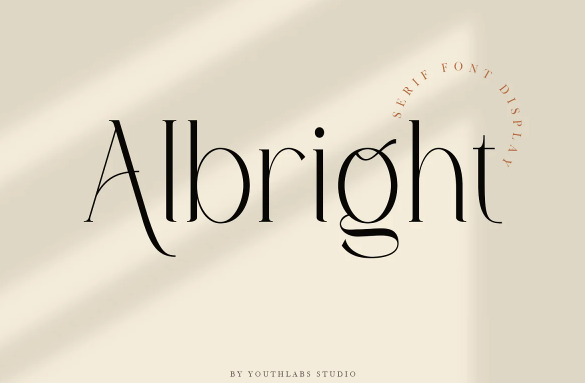
[Creativemarket] Albright Font (2021)
Шрифт Albright - это шрифт SERIF, который демонстрирует современную элегантность с уникальными лигатурами и альтернативами для дизайнера или владельца продукта, которым нужны решения, чтобы их дизайн выглядел более современно и стильно. С помощью этого шрифта вы получите стильные, элегантные и, безусловно, уникальные логотипы.